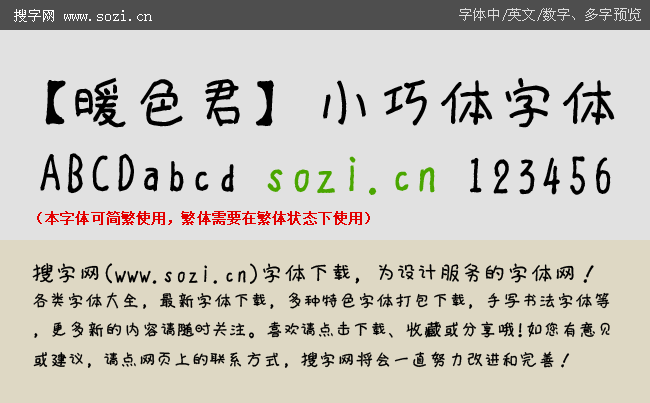
小巧體字體
搜字網(wǎng)給大家提供一款卡通手寫(xiě)風(fēng)格的手機(jī)中文字體下載。名字叫小巧體字體,這款手機(jī)字體是仿照兒童手寫(xiě)風(fēng)格的卡通手寫(xiě)字體,結(jié)構(gòu)帶有POP字體風(fēng)格,特別適合喜歡卡通的朋友在手機(jī)上安裝使用。